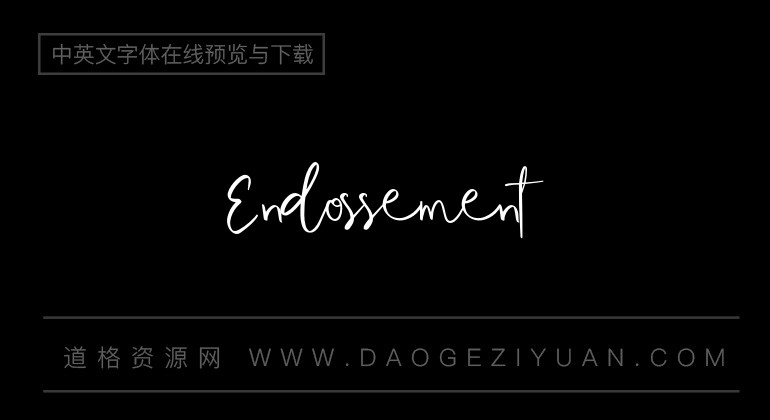
Endossement
Endossement 是一款精致的英文字体,它拥有细腻的曲线和清晰的结构,可以用来制作海报、标志、书籍封面等。它结合了现代风格和传统美学,具有时尚的设计感,能够让您的文字和排版更加精美。Endossement 字体可以让您的文字和排版更加精美,增加您的文章的可读性,并且可以让您的设计更加有趣。
Endossement是一款非常不错的手写艺术字体,具有很好的视觉感,适合于文化类的宣传设计、商业类品牌的广告和产品包装设计以及个性化文字排版等较多场景。